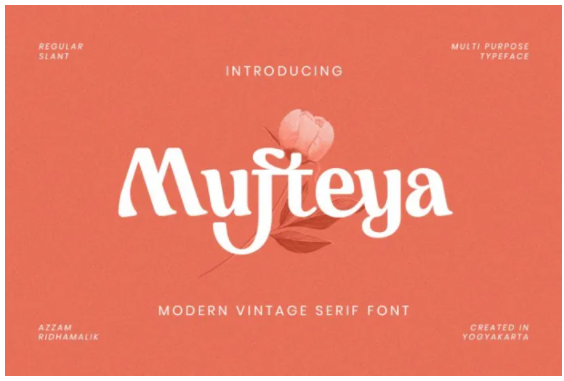
[Fontbundles] Mufteya Font (2021)
Представляем вам шрифт Mufteya, современный шрифт с засечками и некоторыми ретро штрихами, который вы можете комбинировать, чтобы получить любые вариации и уникальные формы всего за несколько секунд. Используйте его как идеальное решение для вашего следующего винтажного логотипа, дизайна макета, винтажного плаката, заголовков журналов или просто как стильное наложение текста на любое фоновое изображение.